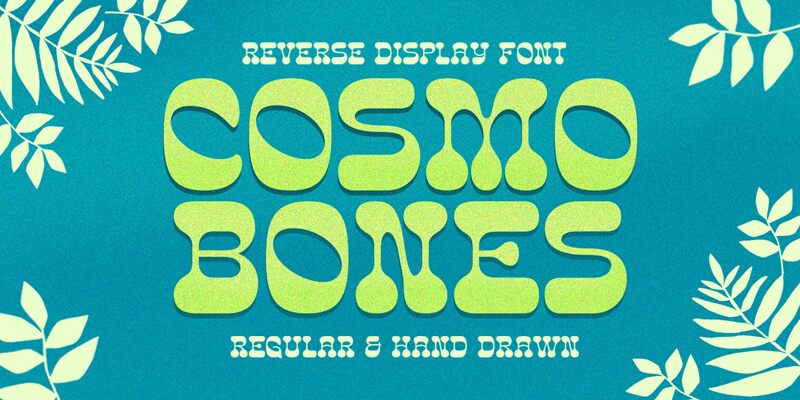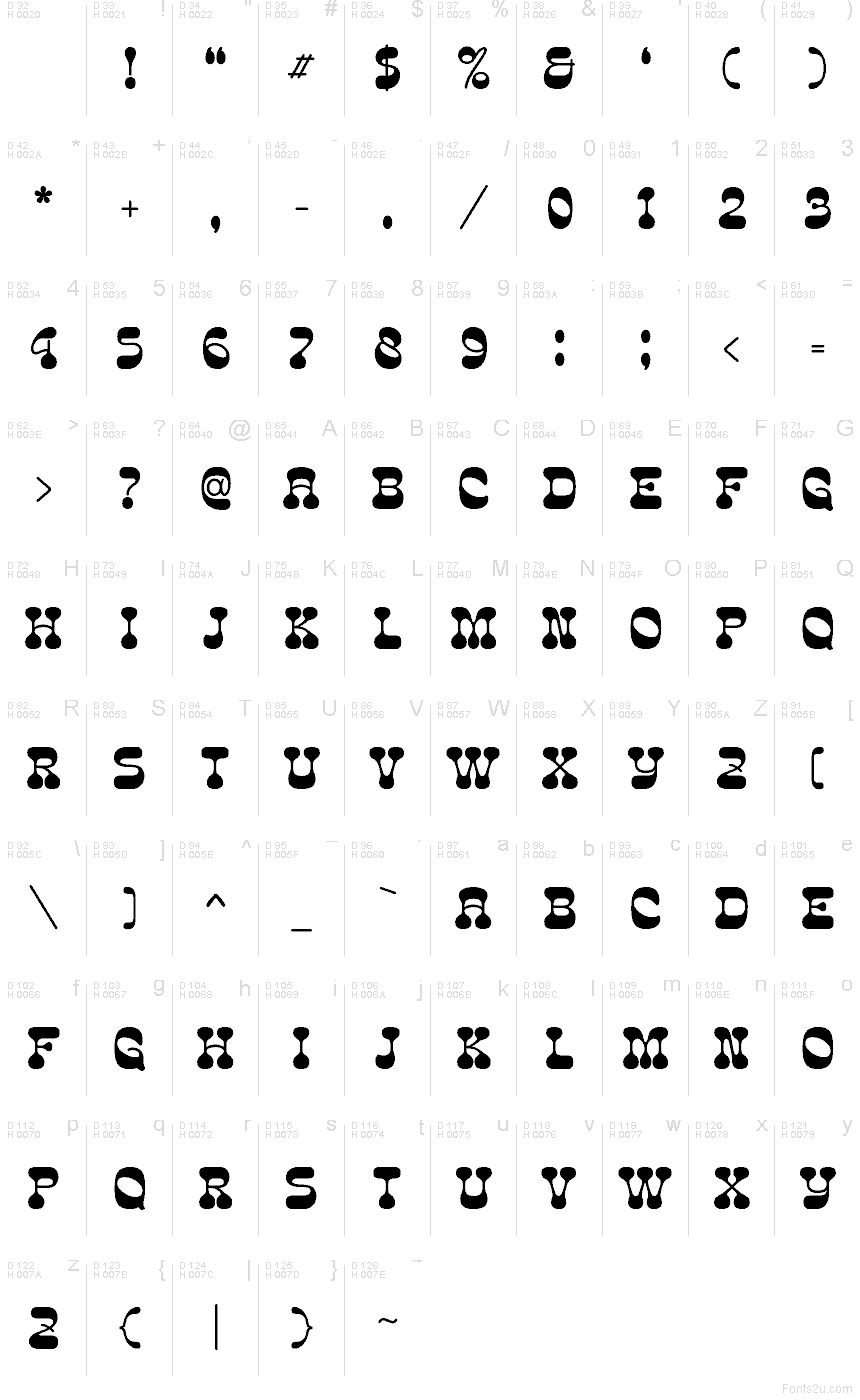
A fonte Cosmo Bones, da Letterhend Studio, é uma tipografia display groovy gratuita com formas arredondadas e fluidas e curvas suaves e infladas. O design remete ao desenho à mão sem perder a clareza, apresentando laços largos e um ritmo suave que confere a cada palavra um visual elástico e vivo.
A Cosmo Bones funciona muito bem em pôsteres, designs musicais, logotipos retrô, embalagens, flyers de eventos e artes marcantes para redes sociais, pois suas curvas suaves carregam um tom decorativo nítido. Esta fonte gratuita também se encaixa perfeitamente em citações curtas, títulos de revistas e projetos de branding que precisem de um acento arredondado e descontraído, sem abrir mão da estrutura.